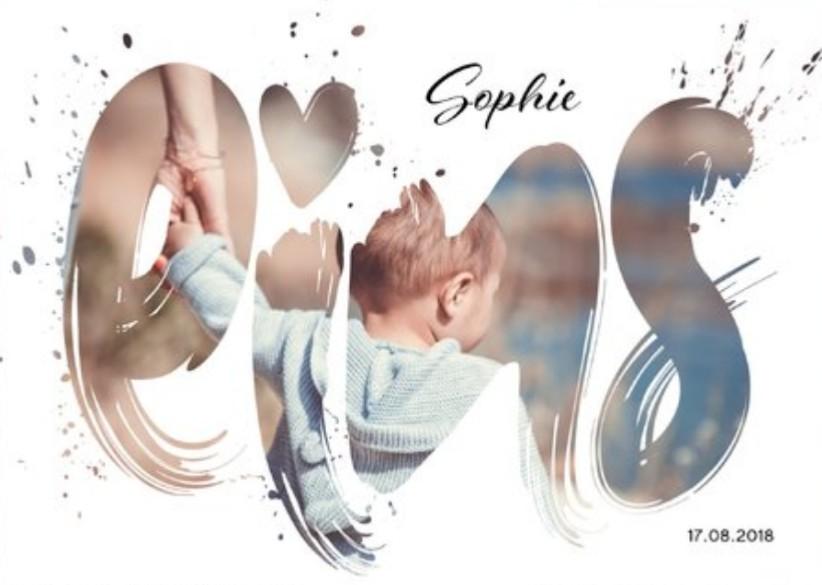
Suche diese ausgefranste Schrift
Hallo, ich bin auf der Suche nach so einer in alle Richtungen ausgefranste Schrift. Oder wie Spritzer. Vielen Dank euch, ich hab mich schon halb tot gesucht :-/
ich hab einfach mal "brush font" bei Herrn Google eingegeben, da werden mir unter "Bilder" so einige angezeigt... Hilft Dir das vielleicht weiter?
Die Farbspritzer sind bestimmt ein Photohop-(kenn den Namen nicht, so fertige "Pinsel"-Spitzen halt, die man importieren und dann anwenden kann). Hier sind ein paar Schriften, die manchmal mit diesem Photoshop-Dingens einherkommen:
Das habe ich natürlich auch schon gesucht. Da gibt's vieles, aber nichts passendes. Ich werde es wohl doch schnell selbst machen. Ich brauche das nur öfter, deswegen hoffte ich, mal etwas fertiges verwenden zu können. Danke natürlich lixh trotzdem! Schönen Abend :-)